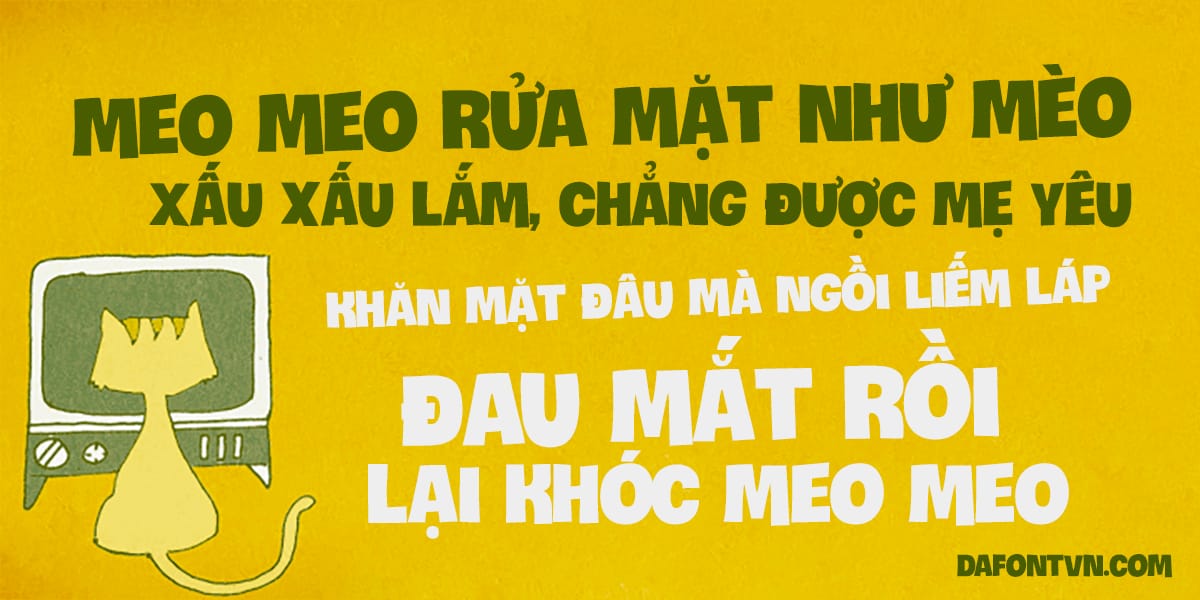
Font iCiel Crocante Việt hóa – Font ấn tượng
Font Crocante Việt hóa là một font chữ hiển thị ấn tượng và hài hước. Bạn có thể sử dụng font chữ này cho rất nhiều thiết kế. Font chữ được Việt hóa bởi iCiel.
Mặc dù là một bảng chữ cái viết hoa hoàn toàn, nó có 2 phiên bản cho mỗi chữ cái, dễ dàng truy cập thông qua các phím trên và dưới của bàn phím. Những mẫu chữ hơi khác nhau này sẽ mang lại sự ngẫu hứng và sức sống cho các thiết kế của bạn. Đảm bảo bạn sẽ ấn tượng đó!